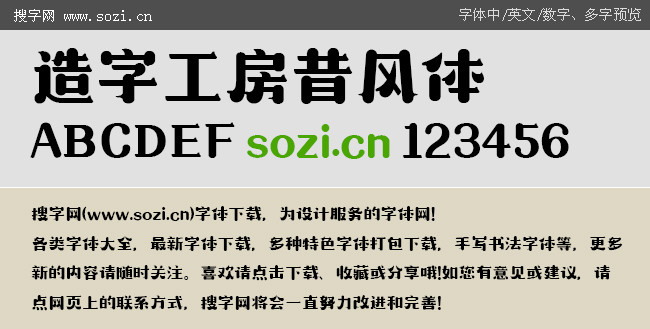
造字工房昔風體
搜字網給大家提供一款造字工房昔風體中文字體下載,造字工房昔風體風格遒勁潤雅,結構隨性自由,筆勢恍如飛鴻戲海,結體嚴緊,筆畫穿插緊密、粗勁圓潤、渾厚寬博,令其筆力恬潤、婉暢又不失端正。適用于海報設計,網頁廣告,書籍封面,包裝設計等應用。(本字體為個人非商用版,如需要商用請聯系官方購買版權)